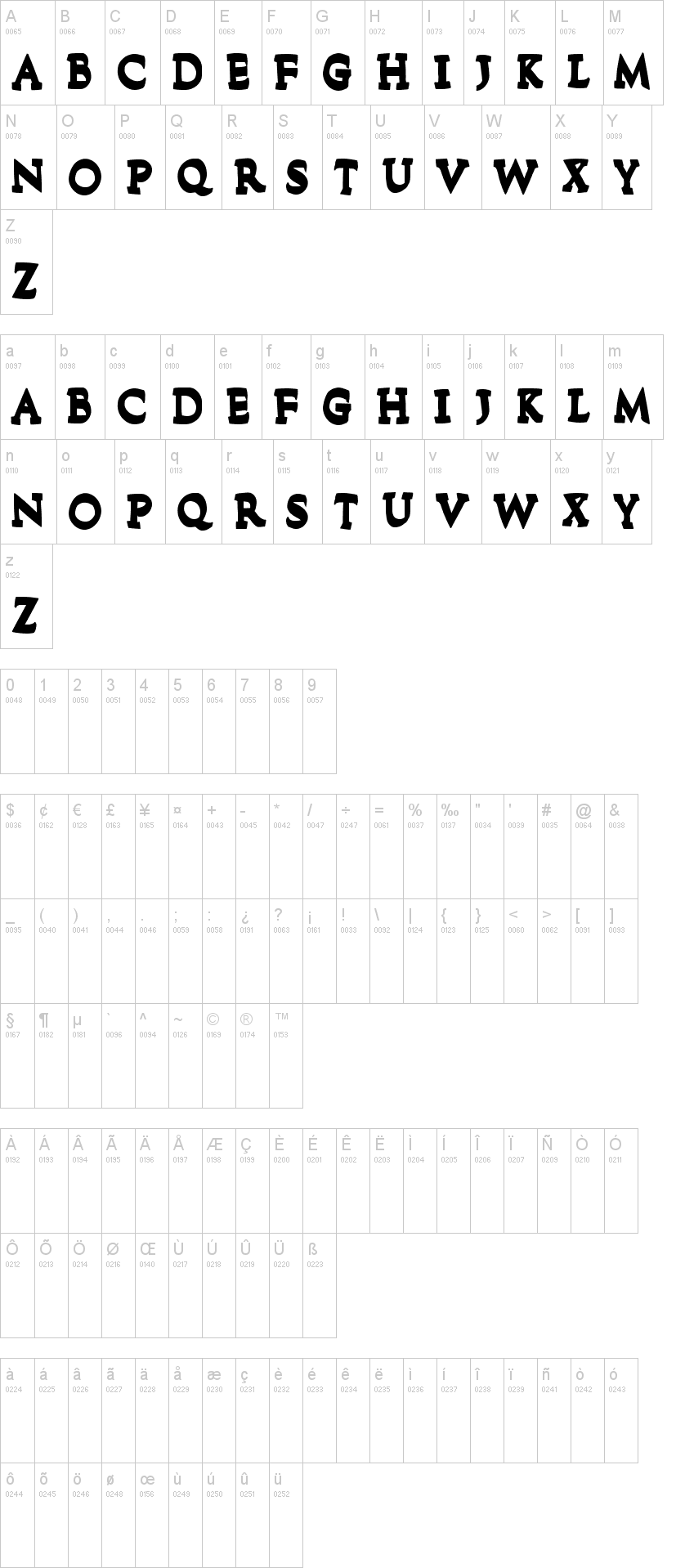
Flood In London
Flood In London 字体是一款拥有英伦韵味的手写字体,由英国设计师 Alex Joganic 创作。字体具有温暖的质感,它的设计风格混合了古典和现代,拥有粗细不一的笔画,每一个字母都具有英伦风情,能够提供极具质感的文字体验。Flood In London 字体支持多种多样的语言,可以用于多种不同的文字排版,让您的文本更加生动活泼。
Flood In London是一款非常不错的手写艺术字体,具有很好的视觉感,适合于文化类的宣传设计、商业类品牌的广告和产品包装设计以及个性化文字排版等较多场景。
Flood In London字符映射图